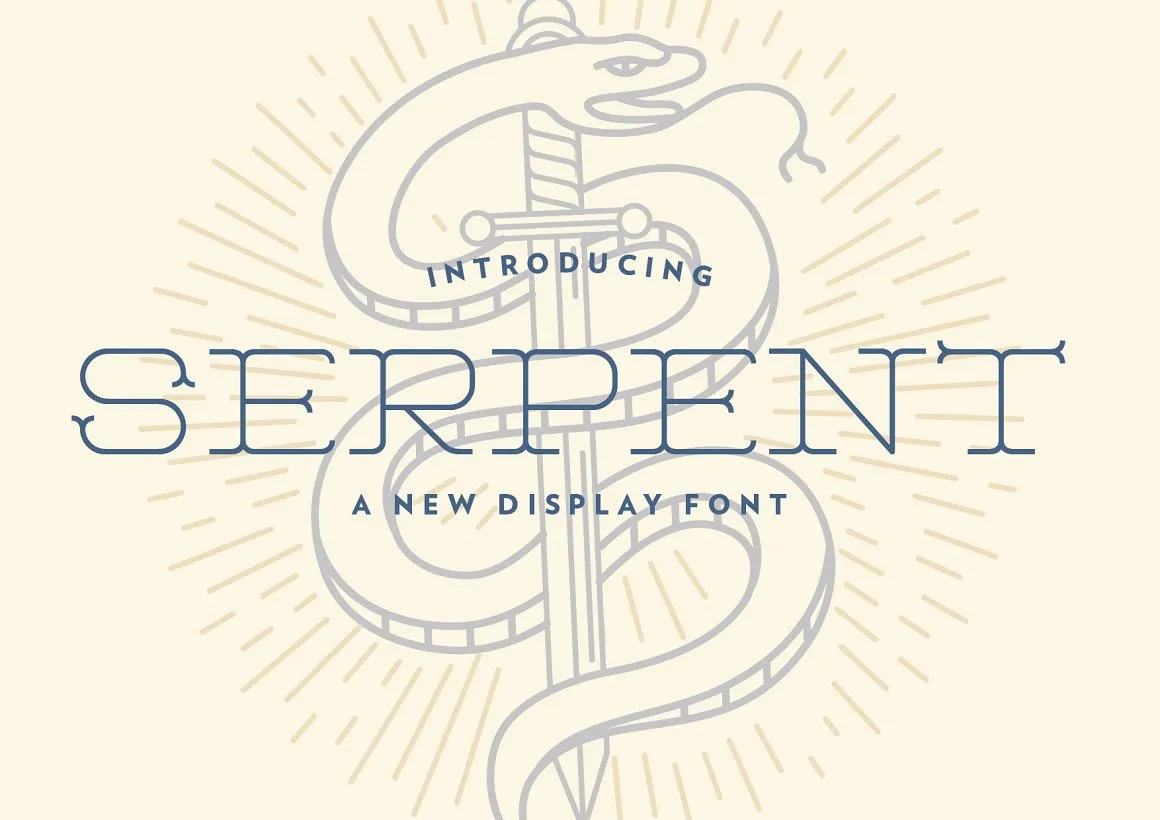
Introduzimos a família de fontes Serpent! Desenvolvida pela Play Dead Studio, essa é uma fonte premium disponível na CreativeMarket. Agora, esta maravilhosa fonte está sendo oferecida gratuitamente para download. Serpent é um tipo geométrico, perfeitamente adaptado para aplicações visuais diversas como design esportivo, logotipos, cartazes, embalagens, material promocional e até mesmo roupas personalizadas. Esta fonte de estilo serif é ideal para projetar elementos gráficos dinâmicos e chamativos. Ela é perfeita para qualquer tipo de mídia visual que desejamos comunicar de maneira impactante e sofisticada. Seja para criar uma identidade visual única ou integrar em materiais promocionais, Serpent oferece um estilo elegante e moderno que certamente não deixará você insatisfeito. Agora é o momento perfeito para se dar ao luxo de adquirir a Serpent Display Font. Essa fonte premium faz parte do catálogo da Play Dead Studio na CreativeMarket, então é uma compra bem-vinda. Ela será um recurso valioso em qualquer projeto gráfico em que você esteja envolvido. Descubra por si mesmo o poder deste tipo e deixe a Serpent transformar seus projetos visuais no que eles realmente devem ser – impactantes e impecáveis.